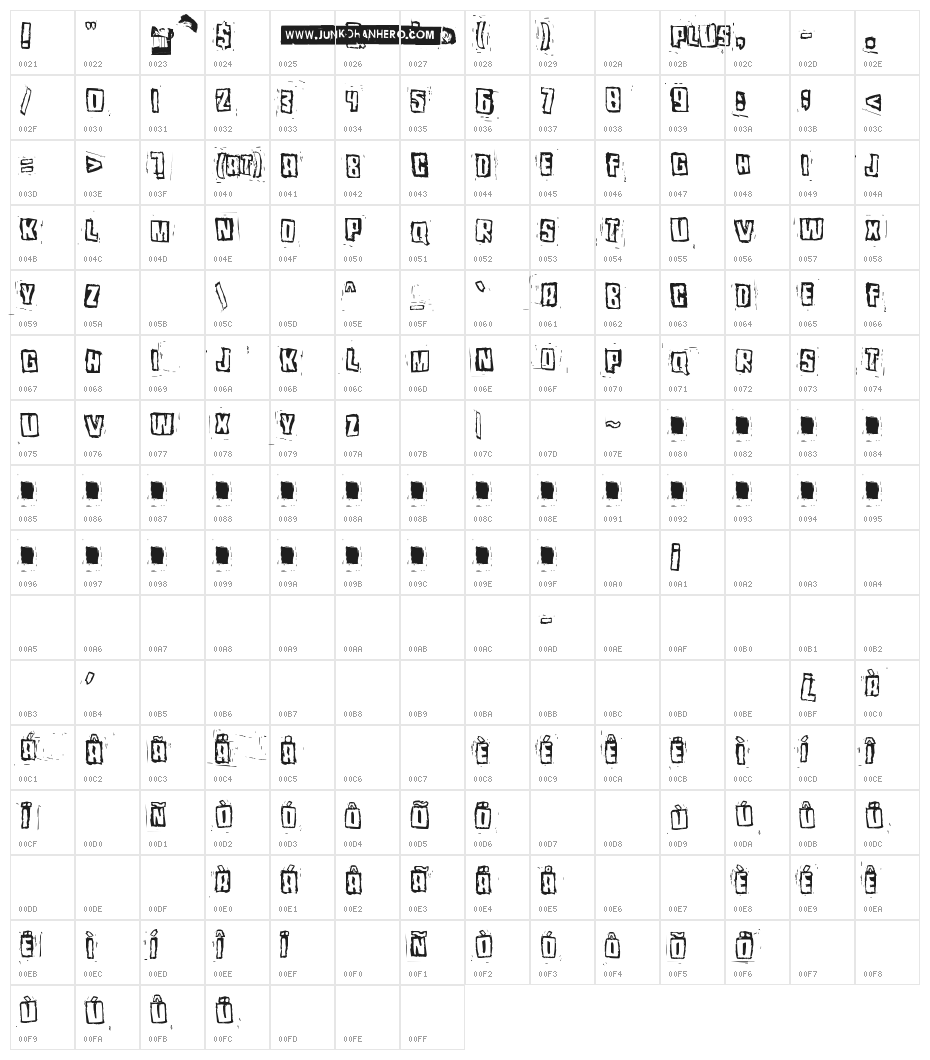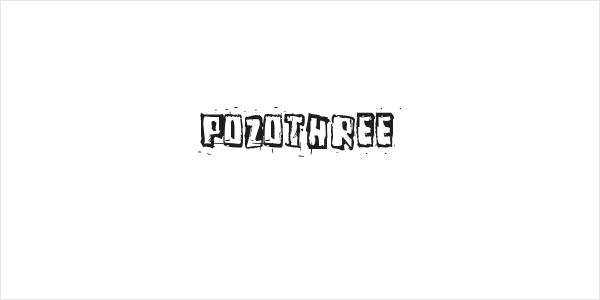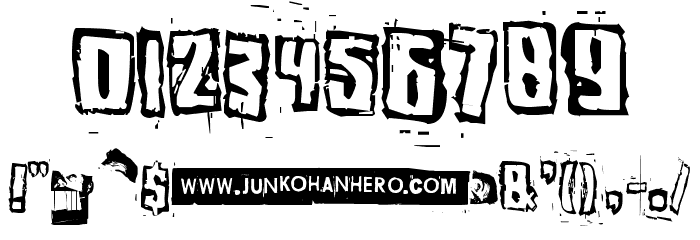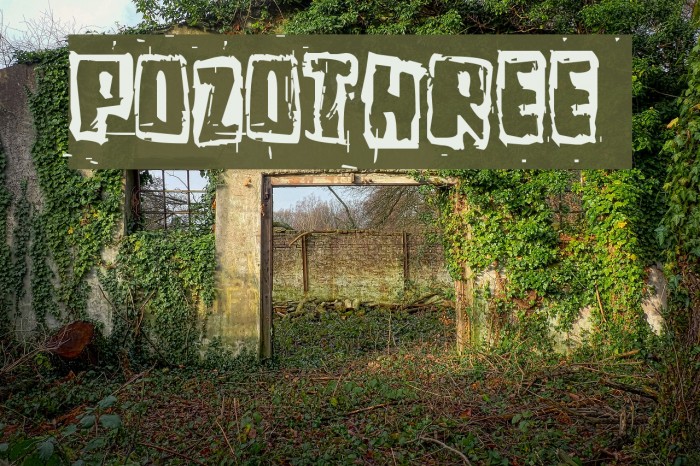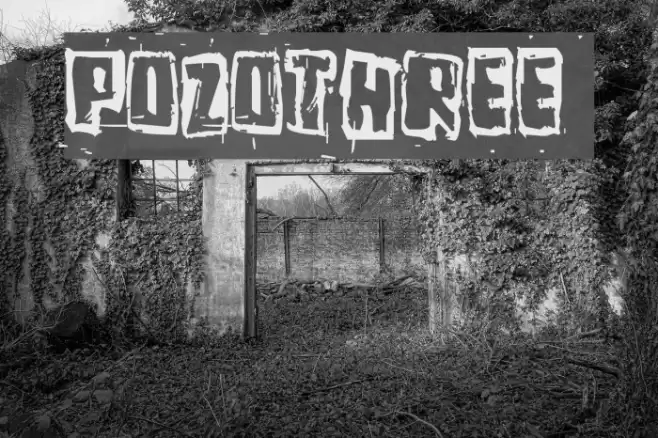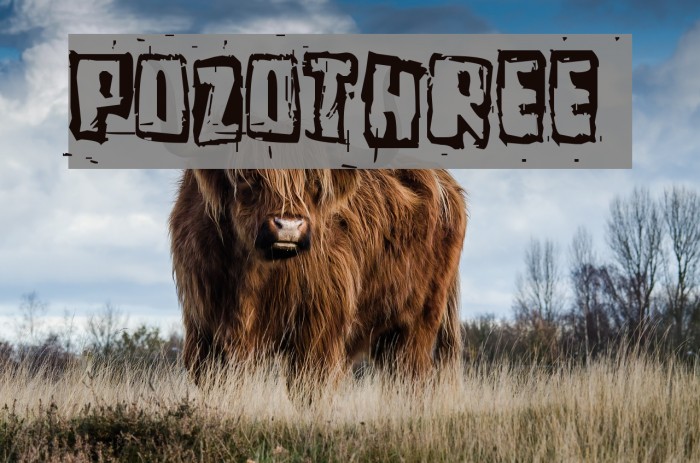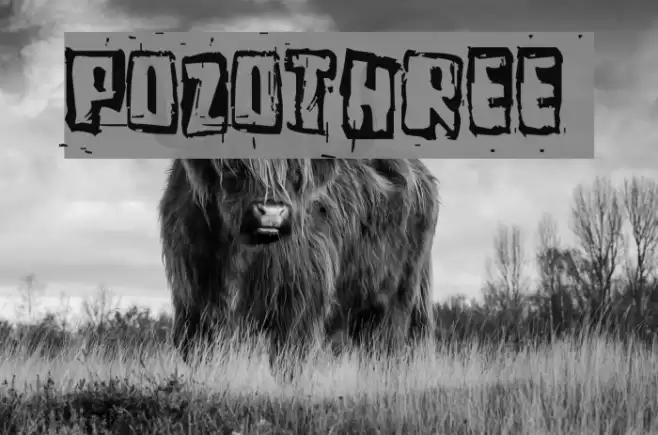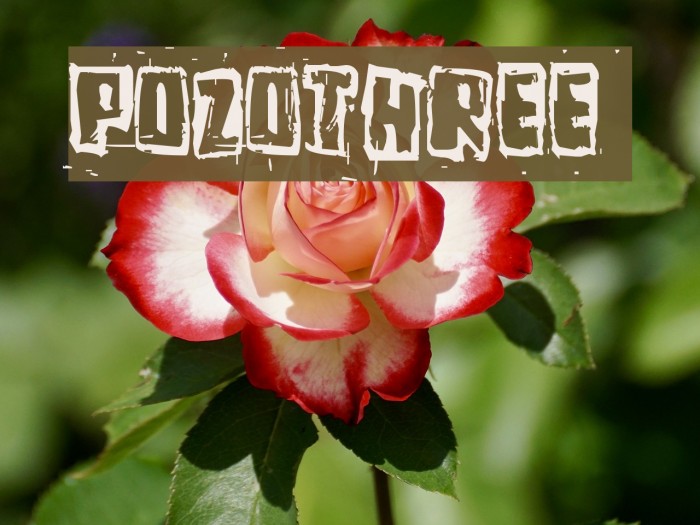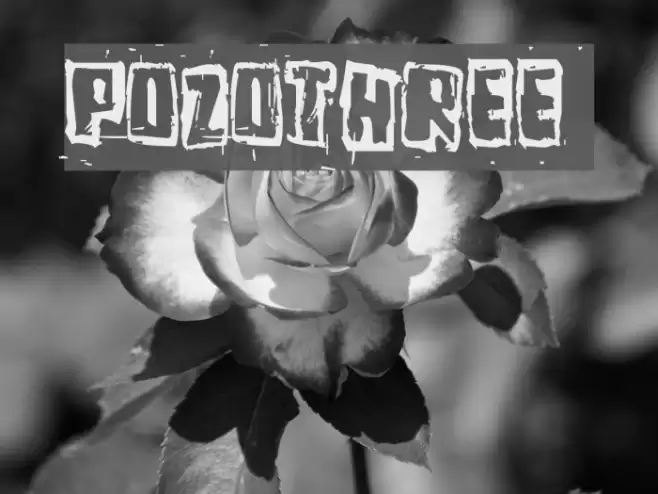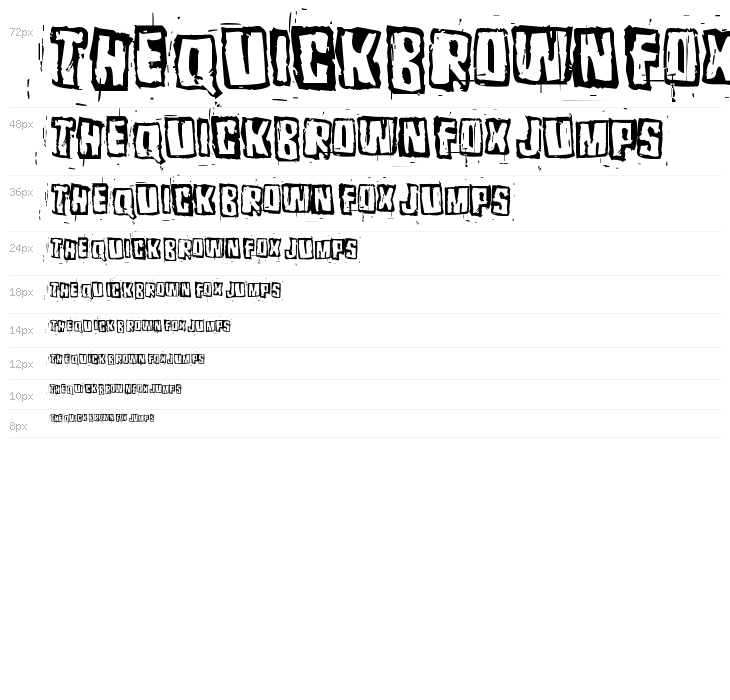
Pozothree Font
✎ Distorted Eroded
| Projets proposés | Ideal for posters, album covers, graffiti art, and any project requiring a bold, edgy aesthetic. |